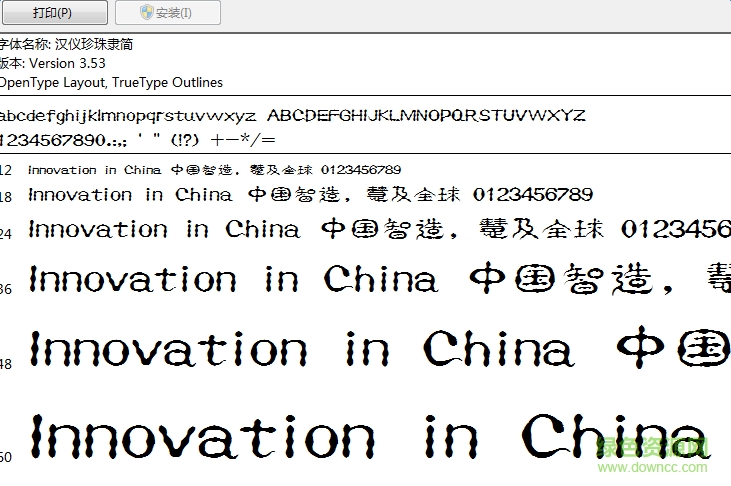
漢儀珍珠隸簡(jiǎn)體
漢儀珍珠隸簡(jiǎn)字體是一款漢儀字體庫中的個(gè)性字體,該字體可以廣泛應(yīng)用于廣告設(shè)計(jì)、宣傳海報(bào)、ppt、影視制作以及任何使用文字的領(lǐng)域,有需要的朋友可以免費(fèi)下載收藏。
小編點(diǎn)評(píng)
漢儀珍珠隸簡(jiǎn)字體是極具個(gè)性的漢儀字體,該字體非常得體大方,整體的效果很出眾,有需要的朋友可以來綠色資源網(wǎng)下載使用!